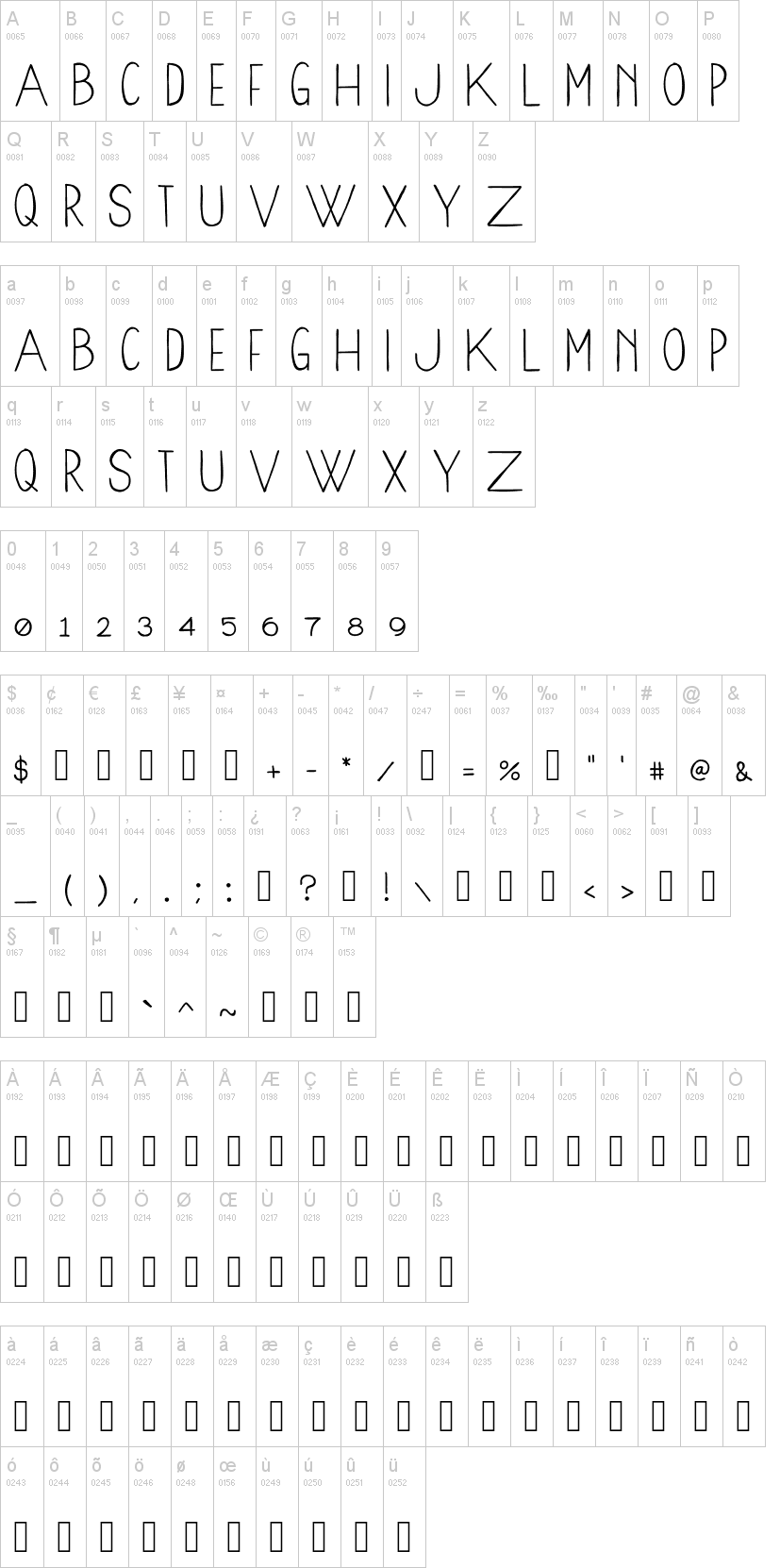
? Wood Cabin 是一款具有柔和古典风格的字体,它具有温暖的效果,适合用于家庭装饰、婚庆、礼物等场合。它的特点是粗细渐变的字体,每个字母之间有一定的距离,使用它可以营造出一种温暖的家的感觉。内容介绍
Wood Cabin是一款非常不错的手写艺术字体,具有很好的视觉感,适合于文化类的宣传设计、商业类品牌的广告和产品包装设计以及个性化文字排版等较多场景。